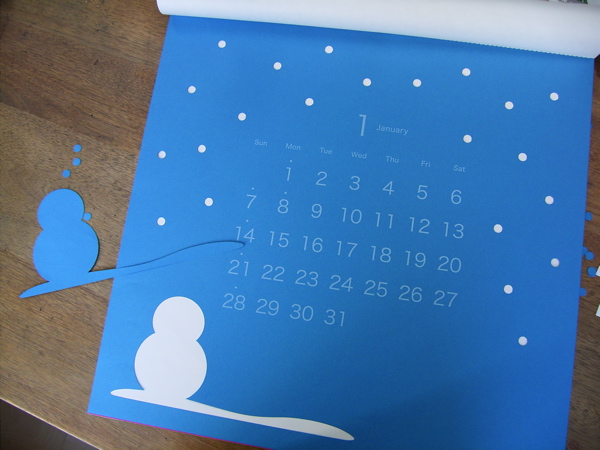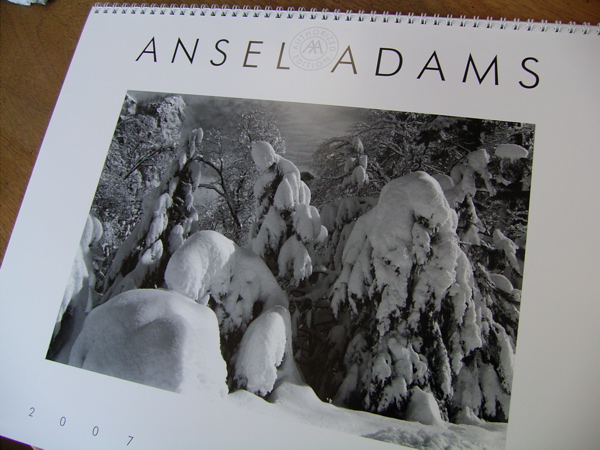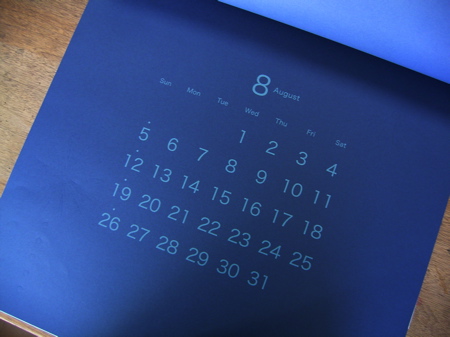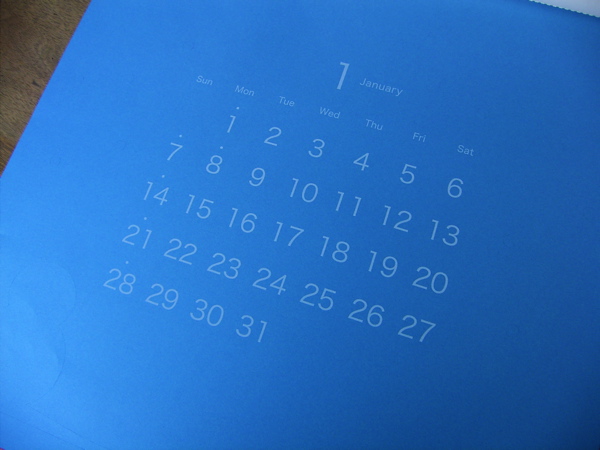
来年のカレンダー
きれいになったお部屋に来年のカレンダーを、もうすでにかけた方もいらっしゃることでしょう。私もようやく仕事部屋の掃除をちょっとだけして(もはや自己満足程度)、新しいカレンダーをかけました。
一年中使うカレンダーは、毎年コレと決めているお宅も多いでしょうね。
我が家のリビングではもう15年以上も前からず〜っとこのアンセルアダムズのカレンダーを使っています。アメリカのヨセミテ国立公園に実際に行ってみて、その自然の美しさにはものすごく感動しました。いつか冬にも行ってみたいなぁ・・・。
このシンプルなモノクロの写真にはいつまでも魅了されています。
なるほど!おもしろーい。ところどころにミシン目があって、空けられる様になっています。しかも毎月そのデザインが違います。
ちなみに、3月はチューリップ、4月は桜、6月は雨だれとカエル、10月はドングリとリス等々・・・。これは毎月あけて行くのが楽しみですねー。
さてさて、大事なのは仕事部屋のカレンダーです。
実際に使いやすいカレンダーを探していましたが、今年は「ほぼにち」のカレンダーを購入してみました。紙なのに書いたり消したり出来るホワイトボードみたいなカレンダーです。
なかなかいいですよ!予定が変更になっても書き換えられるし、白でシンプル、見やすいです。素敵なのは、数字のデザインの素材が毎月変ります。3月はキャベツだし、7月はアルミホイル、11月なんかパンです。ふふふ、カワイイ。
ということで、今年はこれにジャンジャン書いては消して行くことになりそうです。
年末30日に地元のロフトに行き、ほぼにちカレンダーを見てきました。ほ、ほ〜!これはいいかも。と思いました。
そういえば、○月の数字部分は、大橋歩さんのデザインと書いてありました。
今年一年使ってみて、よかったらまたお知らせしま〜す。それにしても大橋歩さんのデザインだったんですね、素敵なはずでした。